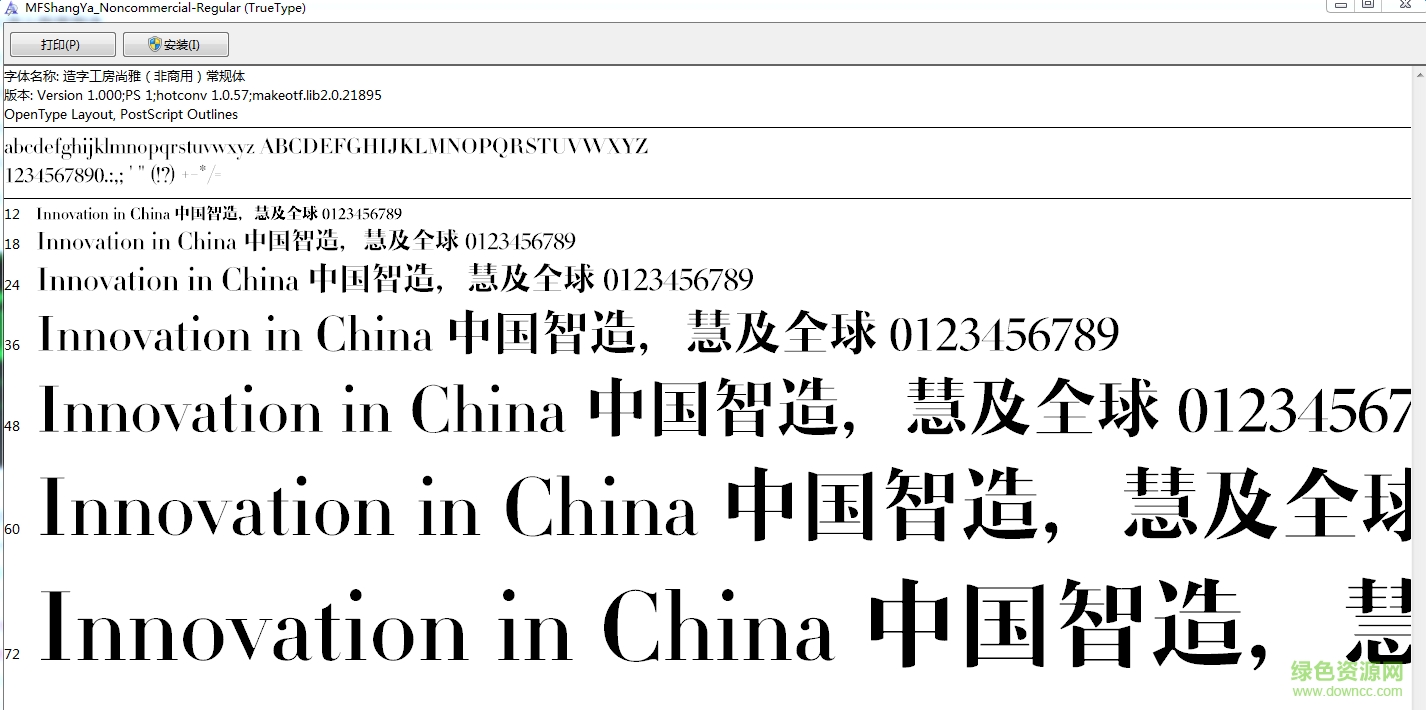
造字工房尚雅宋體是一款造字工房類宋體風格字體軟件,尚雅宋體整體效果剛勁有力,非常的醒目,在標題設計方面有著不錯的應用,同時也深受廣大書法家的喜愛,還有更多好看字體盡情期待,歡迎到綠色資源網下載體驗!
造字工房尚雅宋體比傳統(tǒng)的宋體筆畫較為柔和,整體效果設計簡潔,適合用于期刊設計排版字體、海報設計字體。